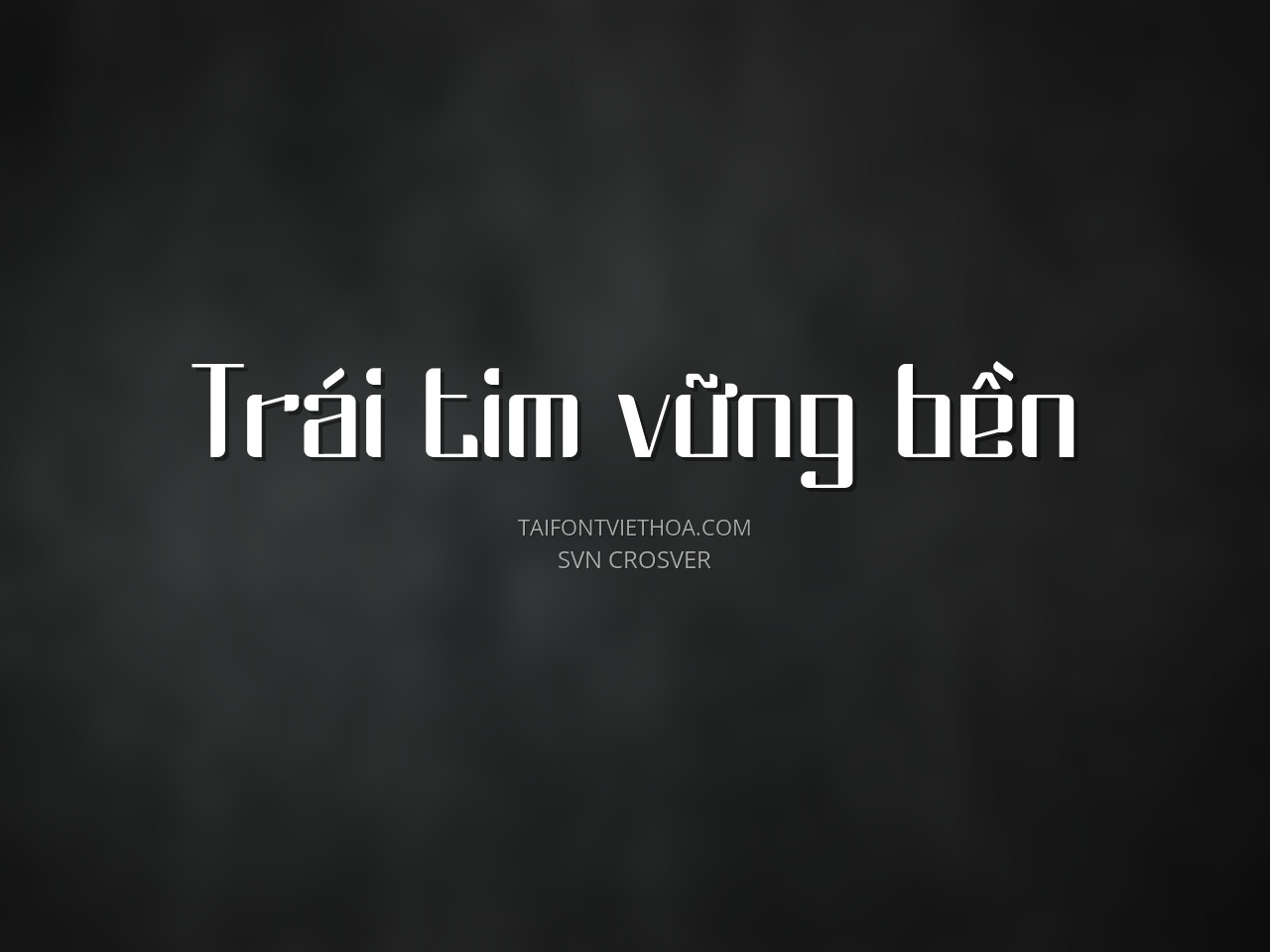
Font việt hóa SVN Crosver
Giới thiệu về font SVN Crosver – Kiểu chữ sans-serif hiện đại, linh hoạt và trẻ trung
SVN Crosver là phiên bản Việt hóa của font Crosver – một kiểu chữ sans-serif mang phong cách hiện đại, linh hoạt và trẻ trung. Font được thiết kế với các nét chữ rõ ràng, cân đối và dễ đọc, phù hợp cho các dự án thiết kế thương hiệu, quảng cáo và truyền thông kỹ thuật số.
Thiết kế sans-serif dễ đọc – Ứng dụng đa dạng trong thương hiệu và quảng cáo
SVN Crosver sở hữu các nét chữ mềm mại, cân đối với thiết kế tối giản và tỷ lệ hài hòa, tạo cảm giác thân thiện và dễ tiếp cận. Font phù hợp sử dụng cho tiêu đề, đoạn văn bản, logo và các ấn phẩm quảng cáo, giúp tăng tính thẩm mỹ và sự dễ đọc trong thiết kế. Phong cách trẻ trung của Crosver rất thích hợp với các dự án công nghệ, giáo dục, thương mại điện tử và truyền thông.
Ứng dụng lý tưởng: thiết kế nhận diện thương hiệu, website, brochure, tài liệu quảng cáo, giao diện người dùng và các sản phẩm kỹ thuật số. Ngành nghề phù hợp: công nghệ, giáo dục, thương mại điện tử, dịch vụ sáng tạo và startup.